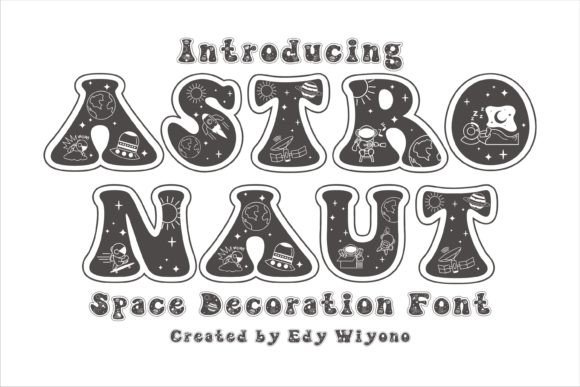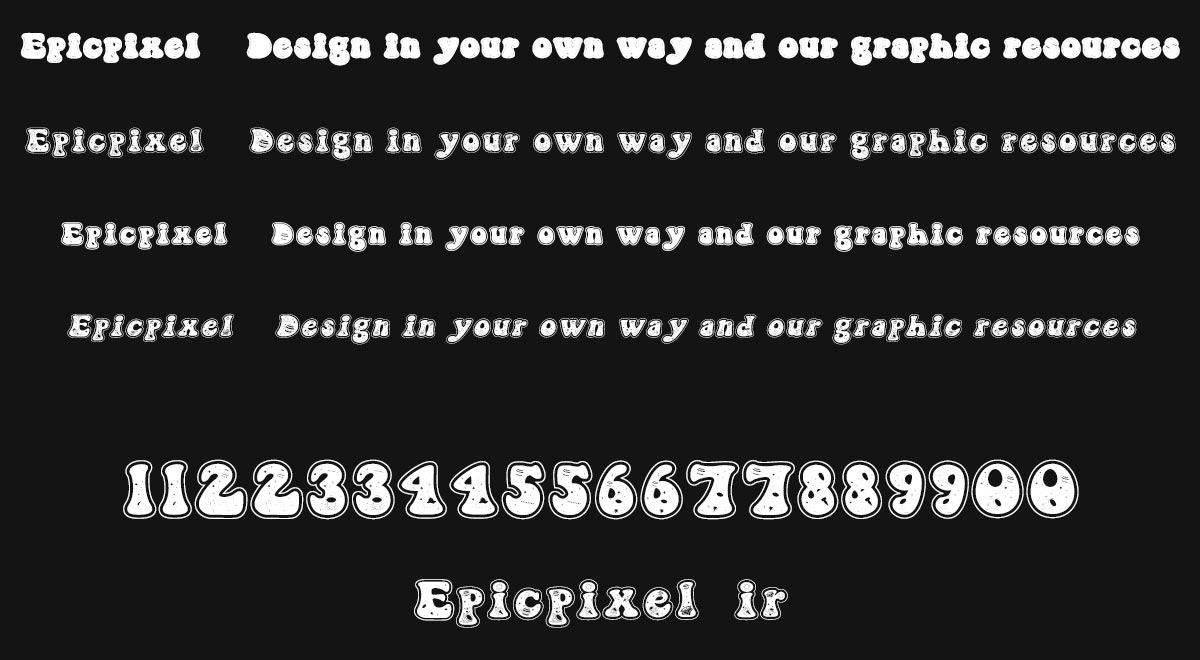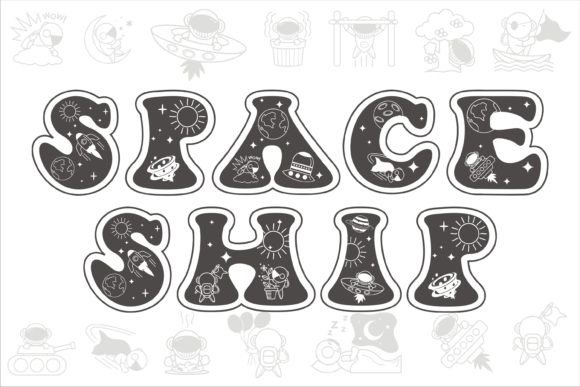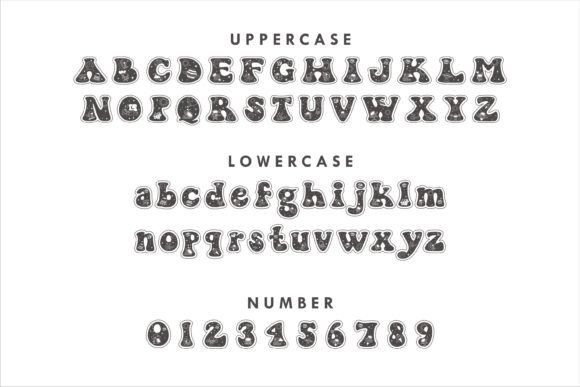
فونت Astronaut انگلیسی
دانلود فونت Astronaut انگلیسی Font استرونوت |
| ⭐ مجموعه فونت | دانلود فونت انگلیسی فضانورد Font Astronaut |
| ⭐ توضیحات | Astronaut یک فونت زیبا با مضامین و شخصیت های کارتونی با فضانوردان و سیاره ما است. این فونت برای طراحی با موضوع آموزش نجوم بسیار زیبا و جذاب است و برای تم های کودکان عالی است. بلافاصله پروژه خود را با یک فونت جذاب کامل کنید. |